دانلود The Modern Collection Font Bundle 100 فونت انگلیسی با طراحی مدرن
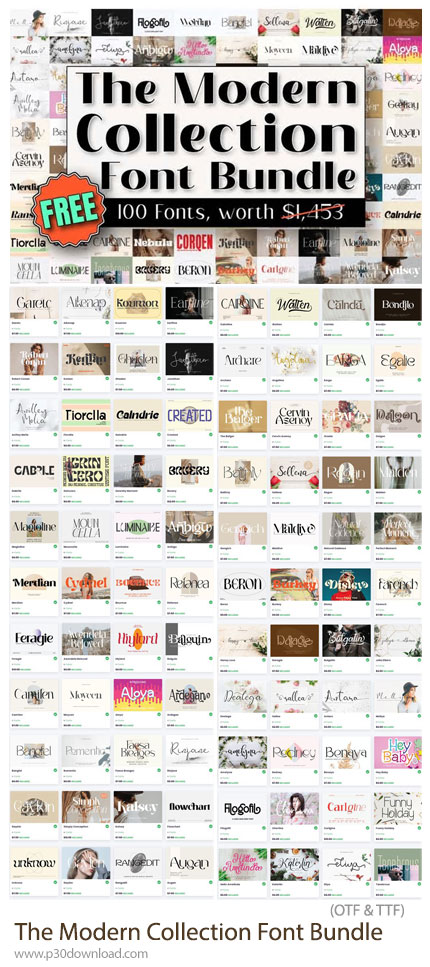
این مجموعه شامل 100 فونت مدرن و حرفهای است که برای طراحان گرافیک، برندینگ، وبسایتها، تبلیغات و پروژههای دیجیتال مناسب میباشد که با فرمت های OTF و TTF بر روی سایت برای دانلود قرار گرفته است. هر فونت با دقت طراحی شده تا هم ظاهر زیبا و هم خوانایی بالا داشته باشد. با این مجموعه میتوانید طراحیهای خود را با سبکهای متنوع و مدرن، برجسته و منحصر به فرد کنید.